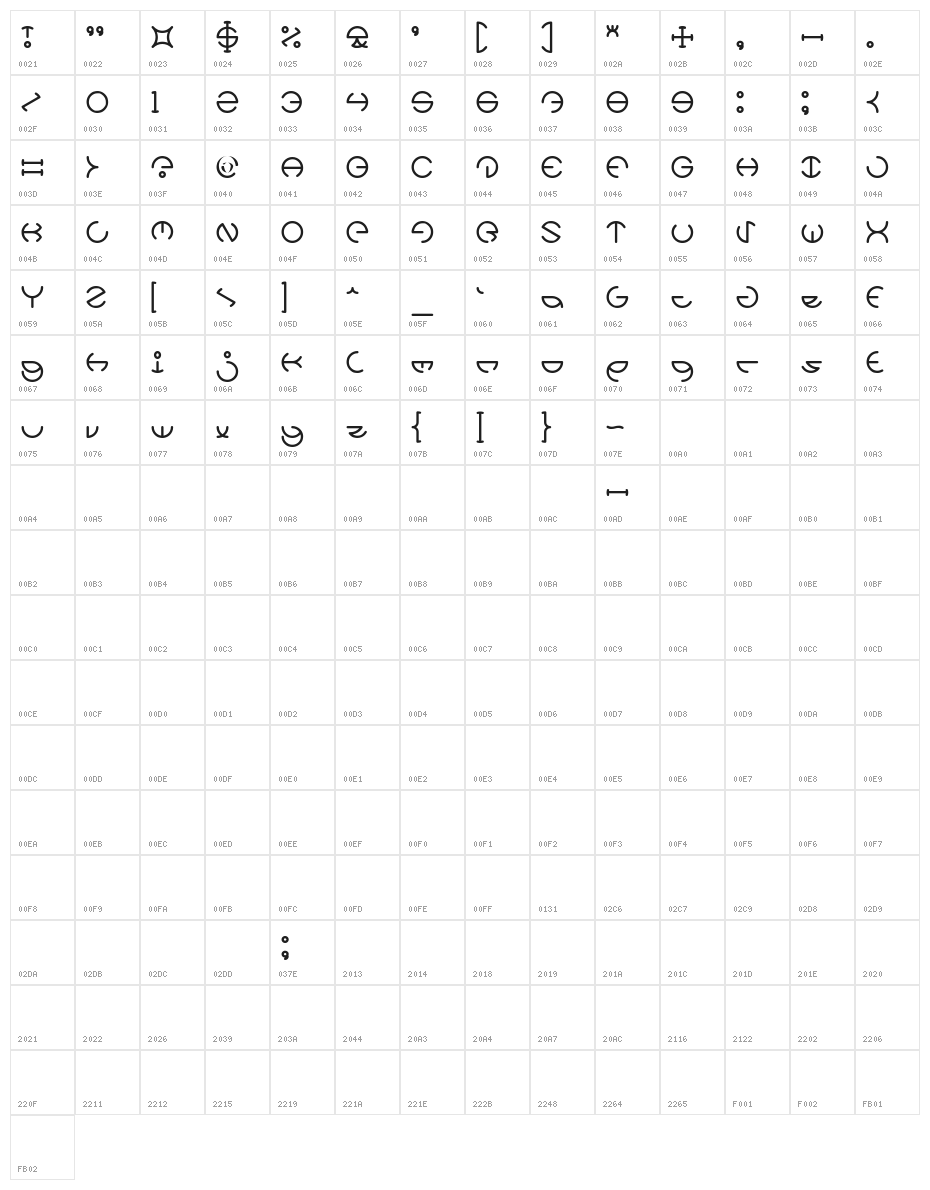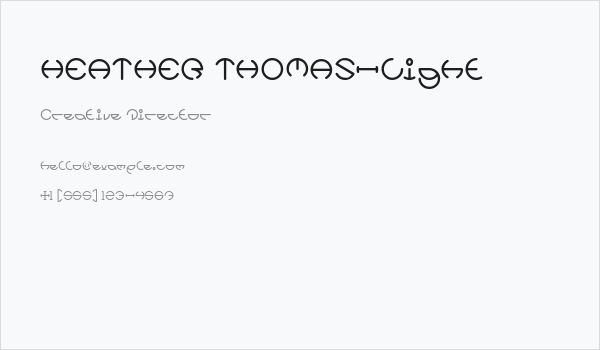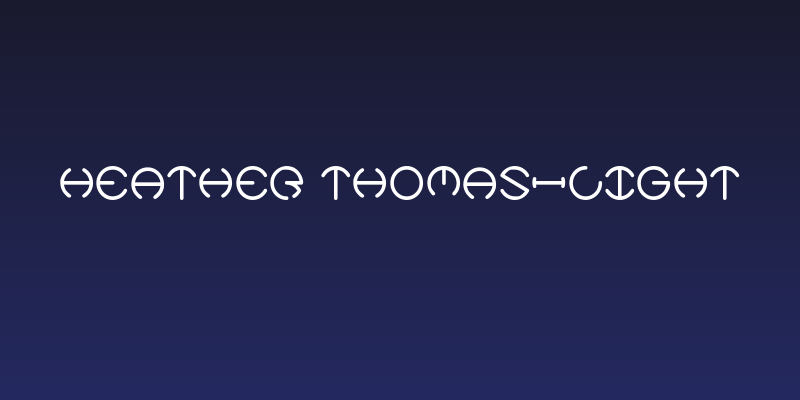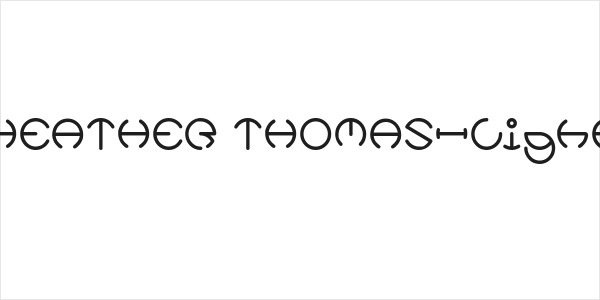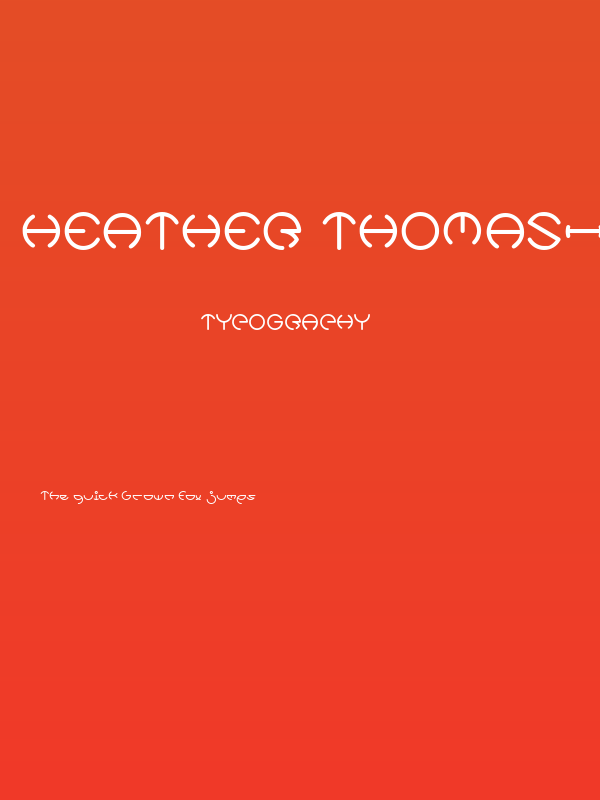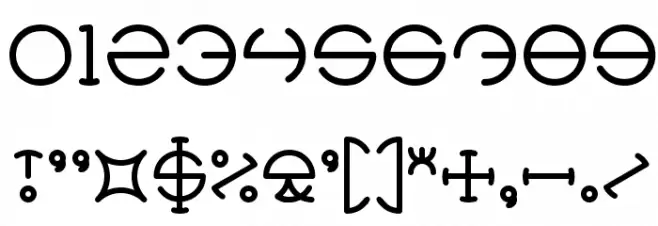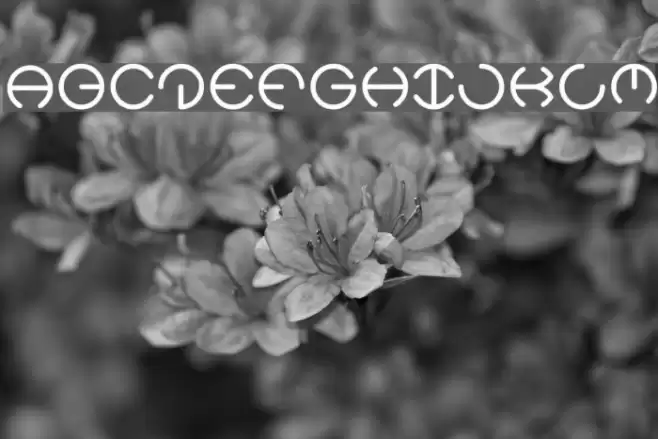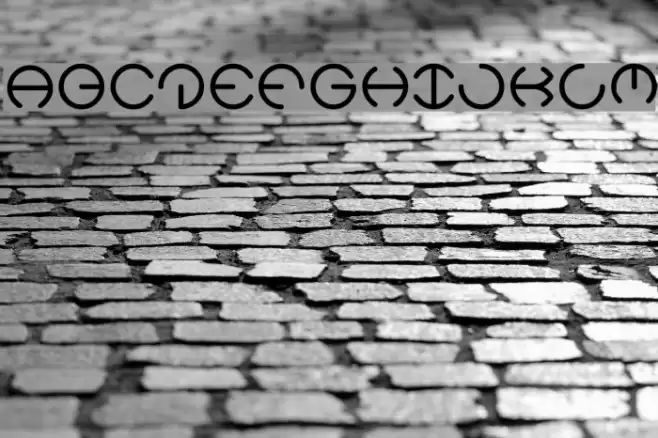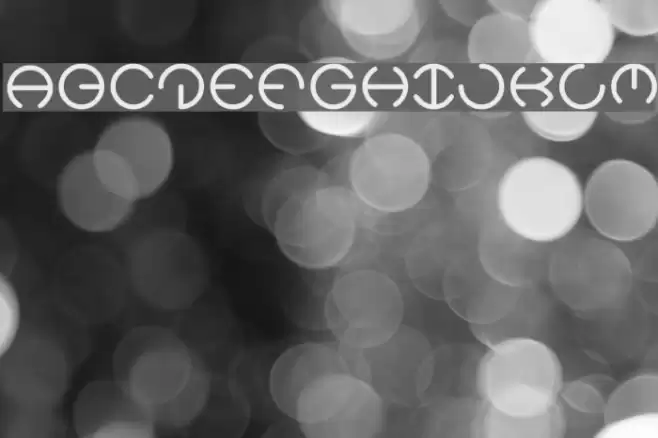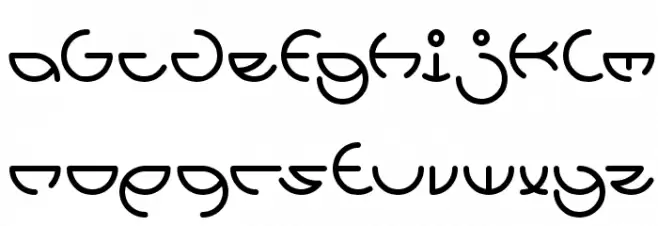
HEATHER THOMAS-Light Font
| おすすめプロジェクト | Ideal for sci-fi themed designs, modern branding, innovative product packaging, and creative digital artwork. |